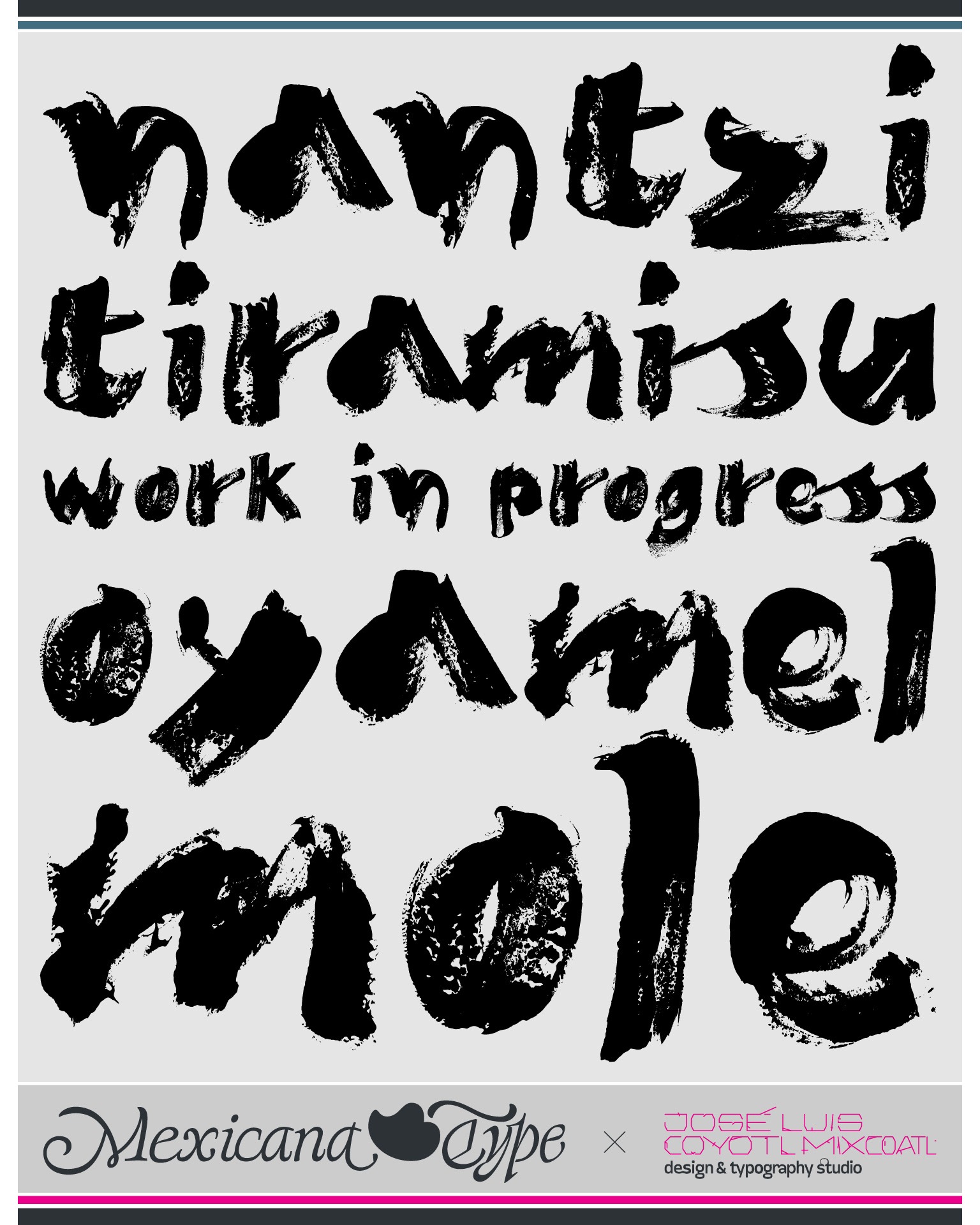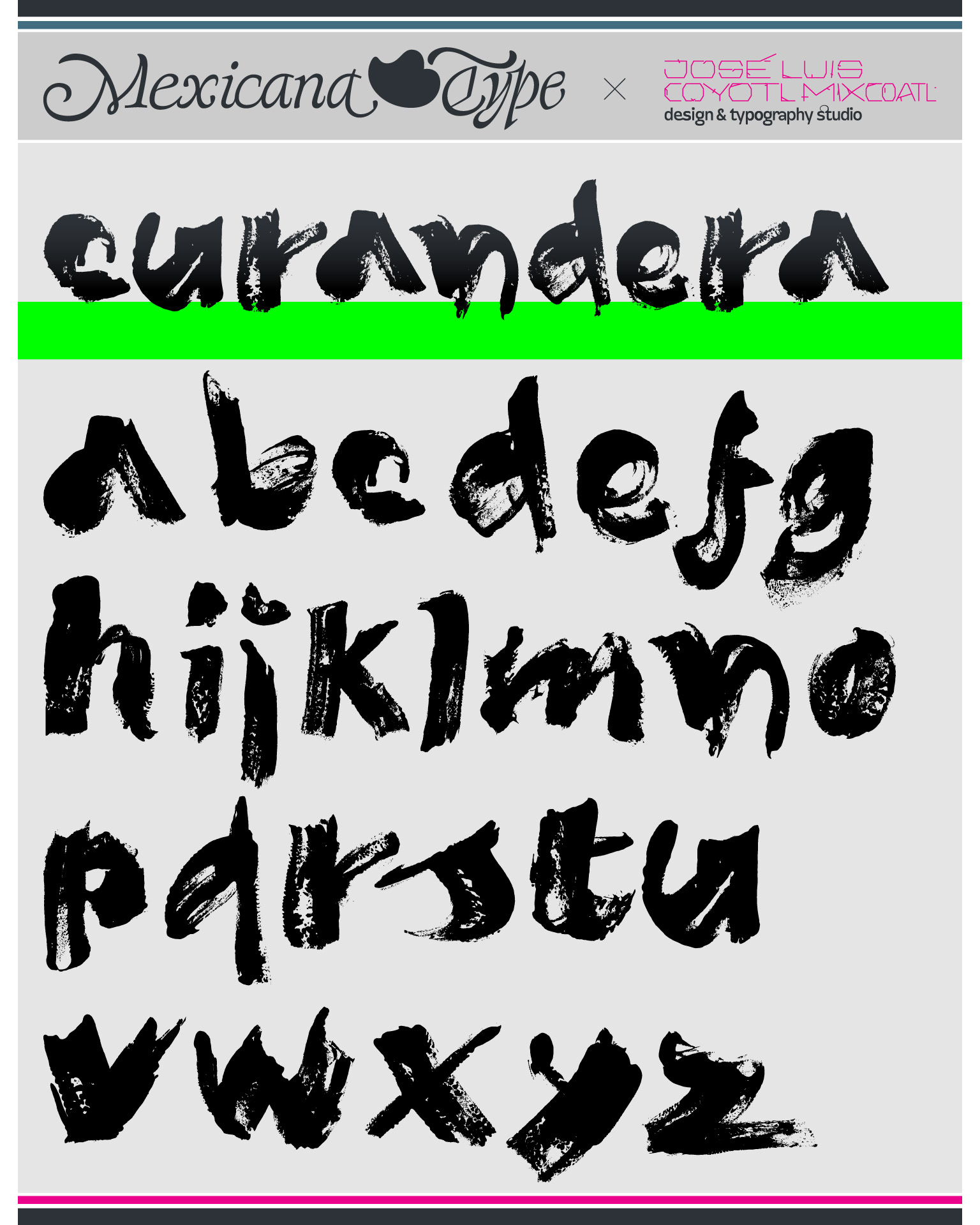
Para el desarrollo de estilo de un poster que estaba diseñando estaba buscando un estilo específico de letras pintadas con una estética cruda y casual. De ahí nació MxT Curandera, de explorar un estilo hjecho a mano, con pintura espesa y brocha seca, con una personalidad un tanto accidentada y de trazo libre.
Si bien se quedó en un proceso de exploración, sirvió también para entender algunas posibilidades estilísticas de formas no tan comunes y de ello generó un set de caracteres limitado a minúsculas/bajas, pero que en la composición tipográfica permitiera darle un sentido informal y texturas ricas en contraformas.